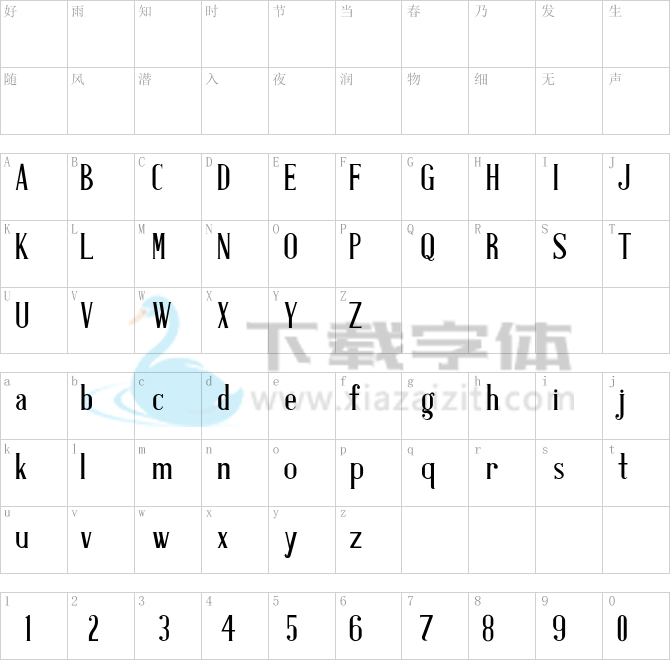
Antique Book Cover Regular.otf字体下载,这款字体结构工整、笔画清晰,兼顾美观与易读性,适用于标题、正文、海报、包装、LOGO 等多种场景。字形优雅稳定,风格百搭耐看,适配日常排版与创意设计,让文字呈现更舒适、更具质感。Antique Book Cover Regular.otf字体下载一笔一画,皆是细节,以均衡的比例、流畅的线条打造舒适视觉体验,字形端正大气,风格简约现代。无论是商业设计、品牌宣传还是日常排版,都能轻松驾驭,让文字更有格调与力量。Antique Book Cover Regular.otf字体下载字体下载。